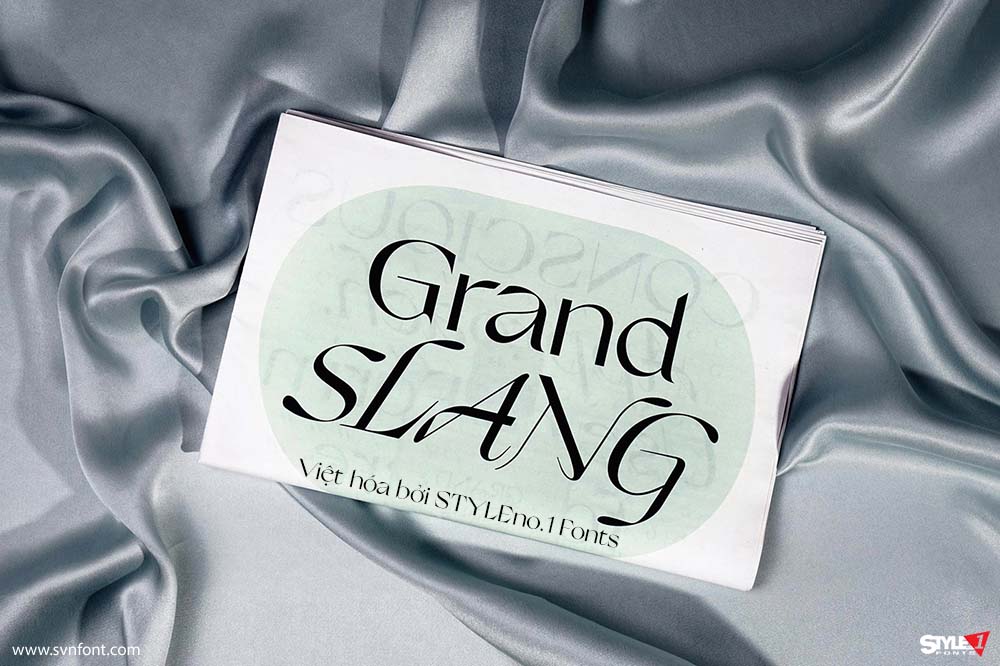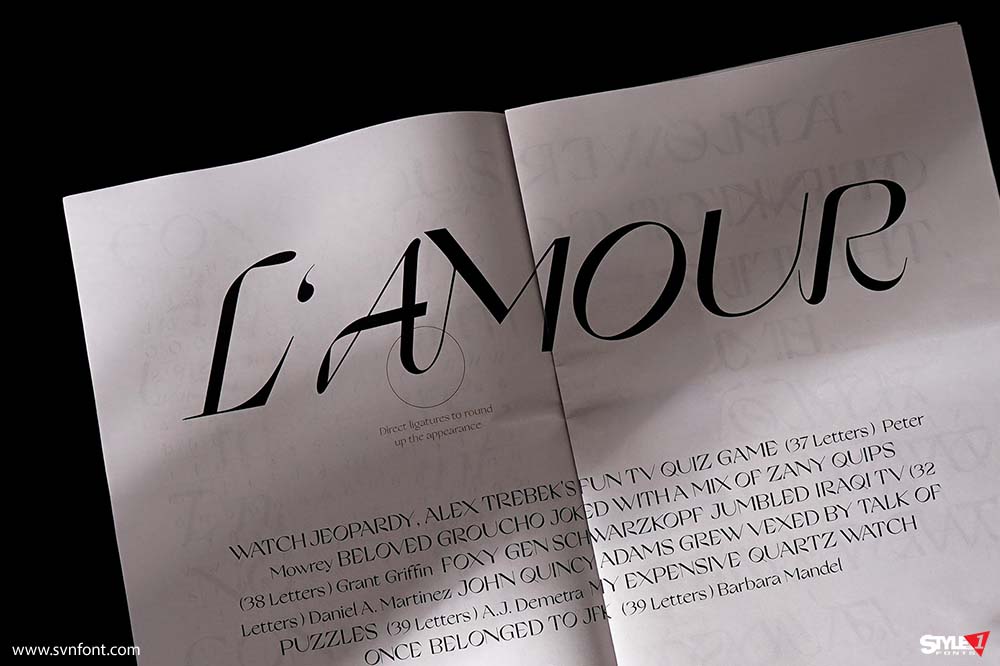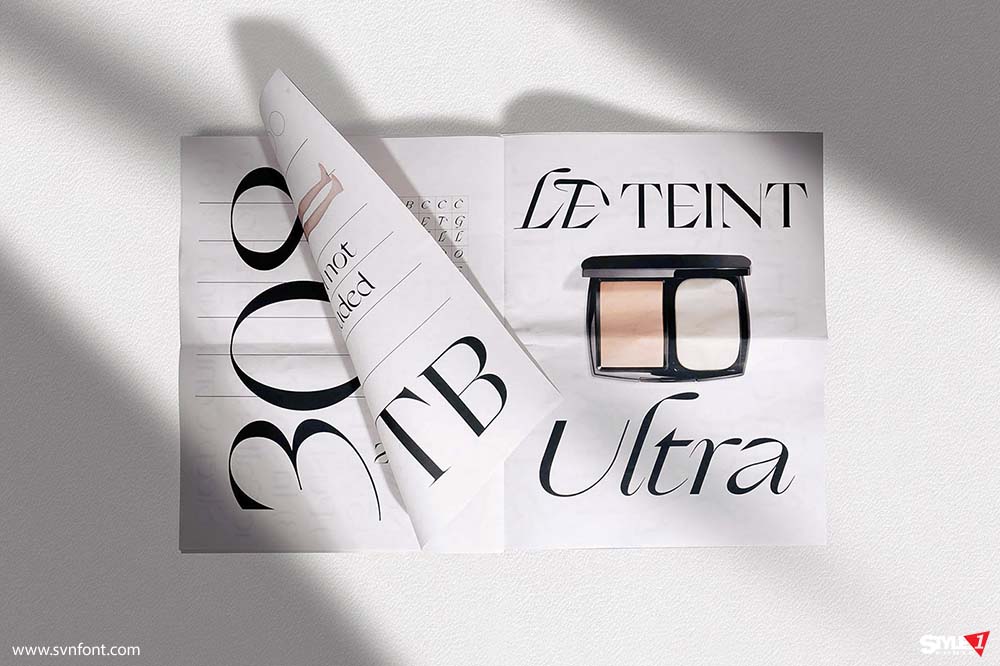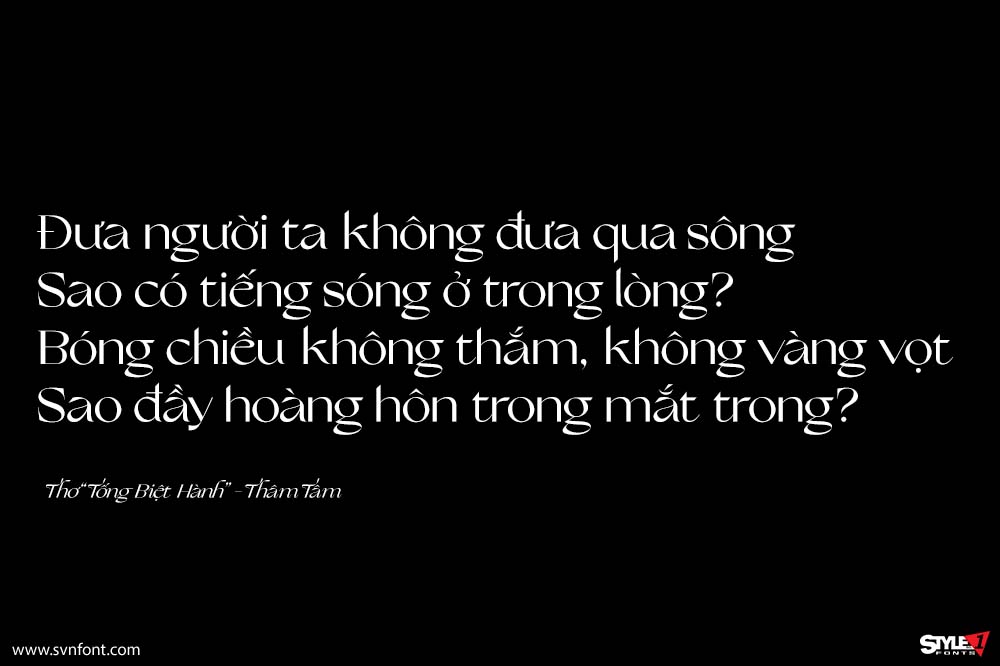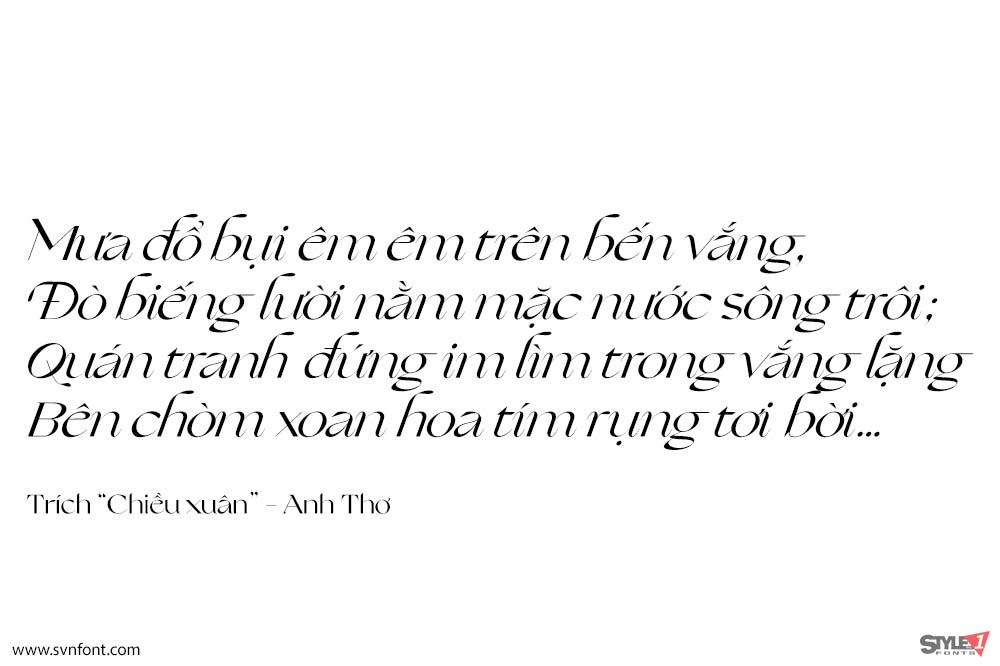
Font Việt Hóa SVN - Grand Slang (2 fonts) Mang Phong Cách Hiện Đại
Grand Slang là một phông chữ mới, mạnh dạn khám phá và định hình lại bản chất của nền thư pháp Mỹ giữa thế kỷ 20 tuyệt đẹp. Mong muốn không thể tránh khỏi không chỉ tái tạo mà còn dịch lại các dạng chữ trong lịch sử, đã dẫn đến việc tạo ra một Grand Slang riêng biệt, kiểu dáng đẹp và giảm bớt.
Truyền lại vẻ đẹp và sự ấm áp của bàn tay trước đây của Oscar Ogg và William A. Dwiggins, Grand Slang đi kèm với một cách tiếp cận lý tưởng để hợp nhất các tạp chí và serifs trong hơn 310 ký tự viết hoa và viết thường riêng lẻ, không theo mô-đun, chữ ghép, hình và dấu hiệu.
Nhà thiết kế: Nikolas Wrobel, B.A.
Nhà phát hành: Nikolastype